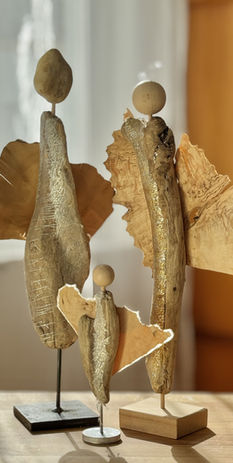
Zur Kalligrafie kam ich über die Malerei. Viele Jahre lang habe ich mich in meiner Freizeit intensiv mit Acrylmalerei beschäftigt und mich durch Kurse an verschiedenen Kunstakademien weitergebildet. Schon damals trug ich den Wunsch in mir, Texte in meine Bilder einfließen zu lassen – doch die Ergebnisse wollten mich nie ganz überzeugen.
So führte mich mein Weg schließlich zu den ersten Kalligrafiekursen. Die strengen Regeln empfand ich anfangs als einengend, bis ich in einem Workshop bei Birgit Nass die kalligrafische Handschrift kennenlernte. Von diesem Moment an war ich in meinem Element. Es faszinierte mich, wie aus kleinen Veränderungen der Handschrift lebendige gestalterische Elemente entstehen können.
Schnell entdeckte ich, dass sich meine neue Leidenschaft wunderbar mit meinem Fundus an Treibhölzern verbinden lässt. Mit Hölzern zu arbeiten, die bereits ihre eigene Geschichte erzählen, und ihnen durch Schrift und Text eine persönliche Note zu verleihen, begeistert mich bis heute. Auch in meine Bilder kann ich inzwischen Texte harmonisch einarbeiten – eine Verbindung von Wort und Form, die mich immer wieder inspiriert.